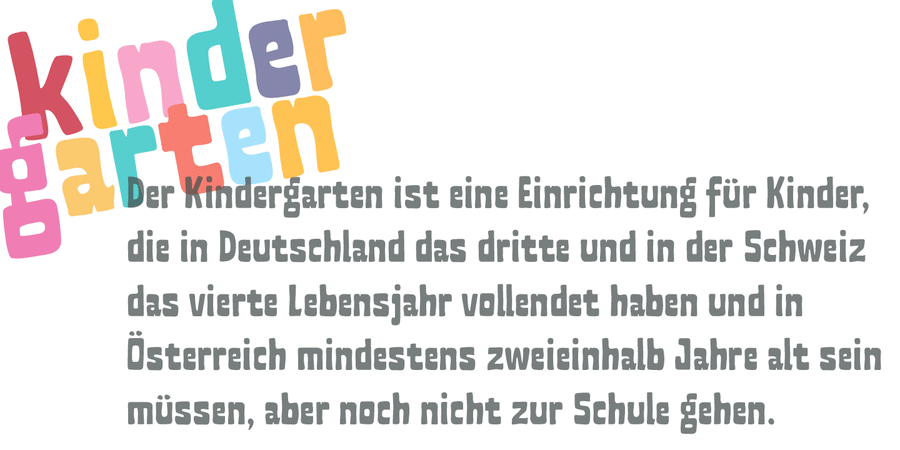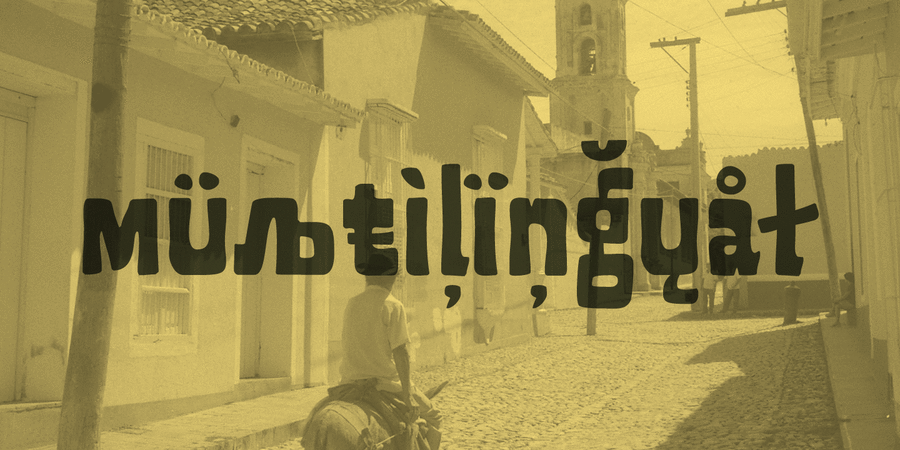
Шрифт Кубинець має грубуватий, але доброзичливий характер. Ідеально підходить для вивісок, упаковки та оголошень. Дивлячись на нього, так і хочеться надягти капелюха й закурити сигару. Шрифт розробив Сергій Ткаченко у 2014 році.
Асоціації з сімейством шрифтів Cubynets 4FОсобистість і характер гарнітури:
ковбойський, старомодний, ремісничий, фермерський, крафтовий, стійкий, якісний, добротний, самостійний, західний, статичний, спекотний, суворий, спекотливий, гучний, дерев'яний, південний, мужній, мачо, наївний, грубий, неотесаний, доброзичливий, потішний, прикольний, рукотворний, дотепний, квадратний, прямокутний, веселий, важкий, помітний, яскравий, тісний, неохайний, грайливий, оригінальний, карикатурний, мультяшний, живий, характерний, нерівний, гулящий, дозвільний, гарячий, вогняний, бандитський, тропічний, артізанальний, вернакулярний, кінематографічний, запальний
стайня, кіно, вестерн, салун, віскі, текіла, сомбреро, алкоголь, сигари, туризм, запряг, сідло, ферма, віз, шериф, ранчо, трактир, родео, кінь, ремесло, коваль, м'ясо, кузня, револьвер, ковбой, піцца, гумор, тютюн, хенд мейд, дитяча книжка, анімація, їжа, закуска, атракціон, цирк, спеції, гра, зоомагазин, тварини, відпочинок, мультфільм, обід, вечеря, базар, графіка, ілюстрація, бик Гарнітура має ознаки стилів: